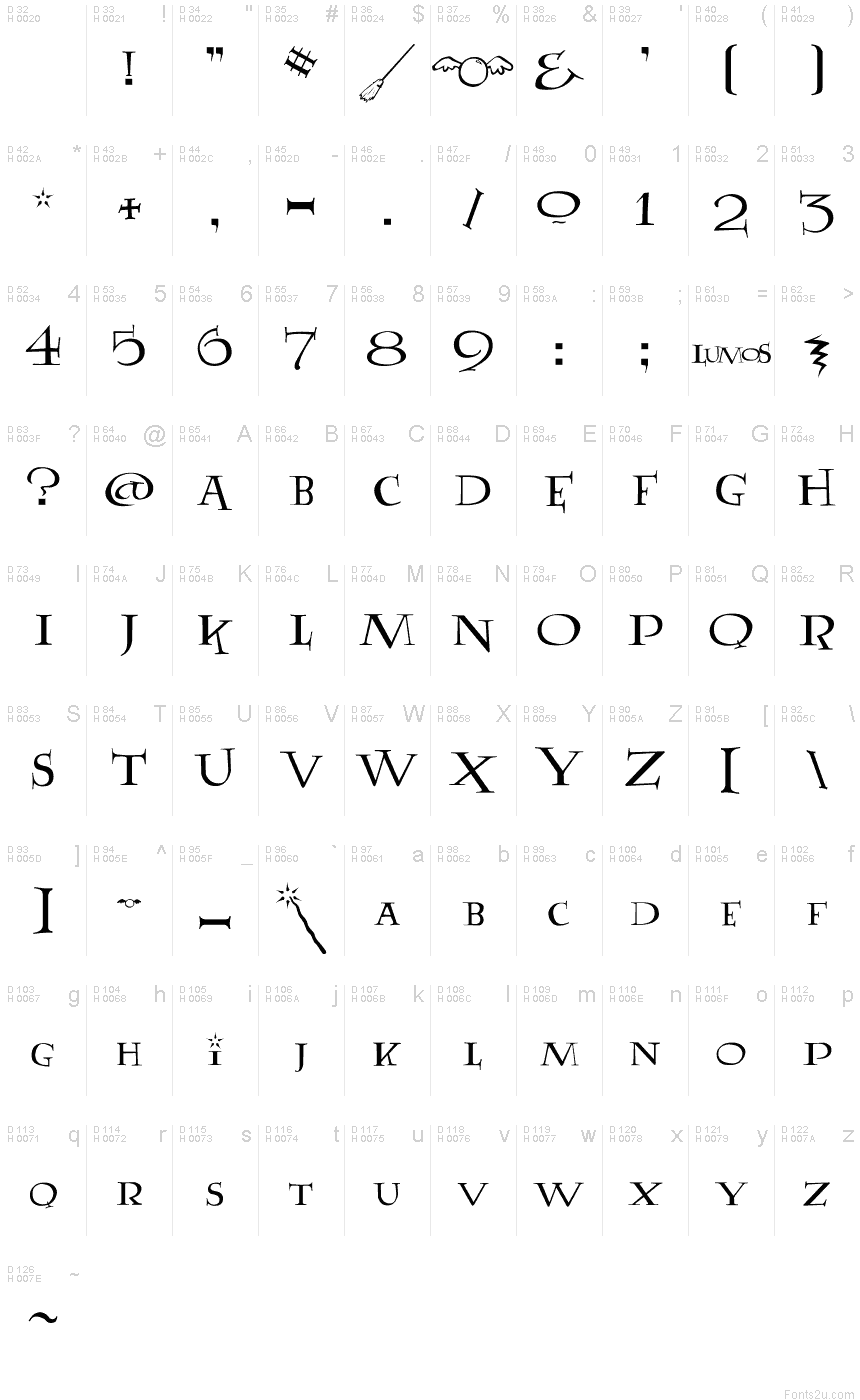
Lumos od Carpe Saponem Fonts to darmowy szeryfowy font typu display, utrzymany w stylu rzymskich inskrypcji, z ostrymi, kontrastowymi literami. Wąskie kształty, spiczaste szeryfy i długie, zwężające się pociągnięcia nadają krojowi formalny, „wykuty w kamieniu” charakter, unikając przy tym zbędnych zdobień.
Lumos świetnie sprawdza się w tytułach książek, brandingu fantasy, oznaczeniach muzealnych, plakatach oraz logotypach inspirowanych dziedzictwem kulturowym, gdzie liczy się klasyczny ton. Ten darmowy font doskonale pasuje również do nagłówków zaproszeń, tytułów w czasopismach i dekoracyjnych podpisów, ponieważ jego wyrazista szeryfowa struktura nadaje krótkim tekstom wyrafinowany, starodawny klimat.
Lumos